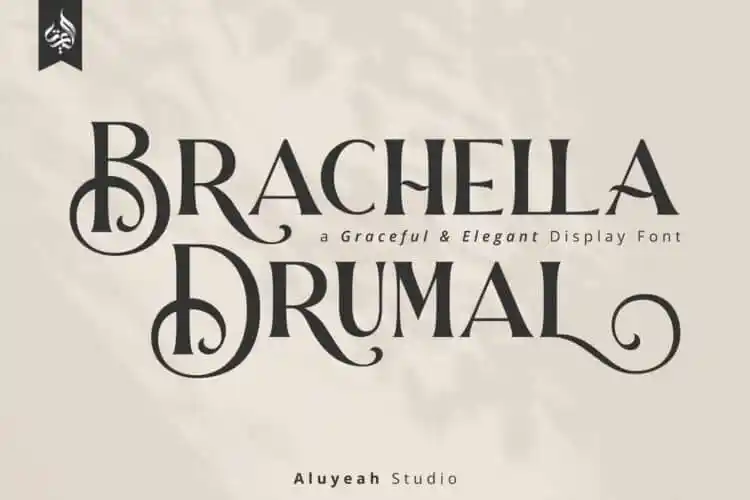
A Barchella Drumal Display Font é uma fonte serifada moderna e peculiar, que oferece inúmeros ligantes para criar designs únicos e atraentes. Criada pelo artesão de fontes chamado Aluyeah Studio, esta fonte traz mais de 30 alternativas estilizadas para tornar o seu design ainda mais místico, elegante e sofisticado. A Barchella Drumal é perfeita para usar em desenhos de logotipo, banners web de moda, promoções de músicos ou promotores de bares ou cafeterias. Ela é versátil o suficiente para muitas aplicações interessantes, tornando-a uma fonte ideal para designers que procuram algo além da norma no design digital. Com sua simplicidade e modernidade, a Barchella Drumal oferece um toque distintivo que certamente deixará seu trabalho mais chamativo e memorável.